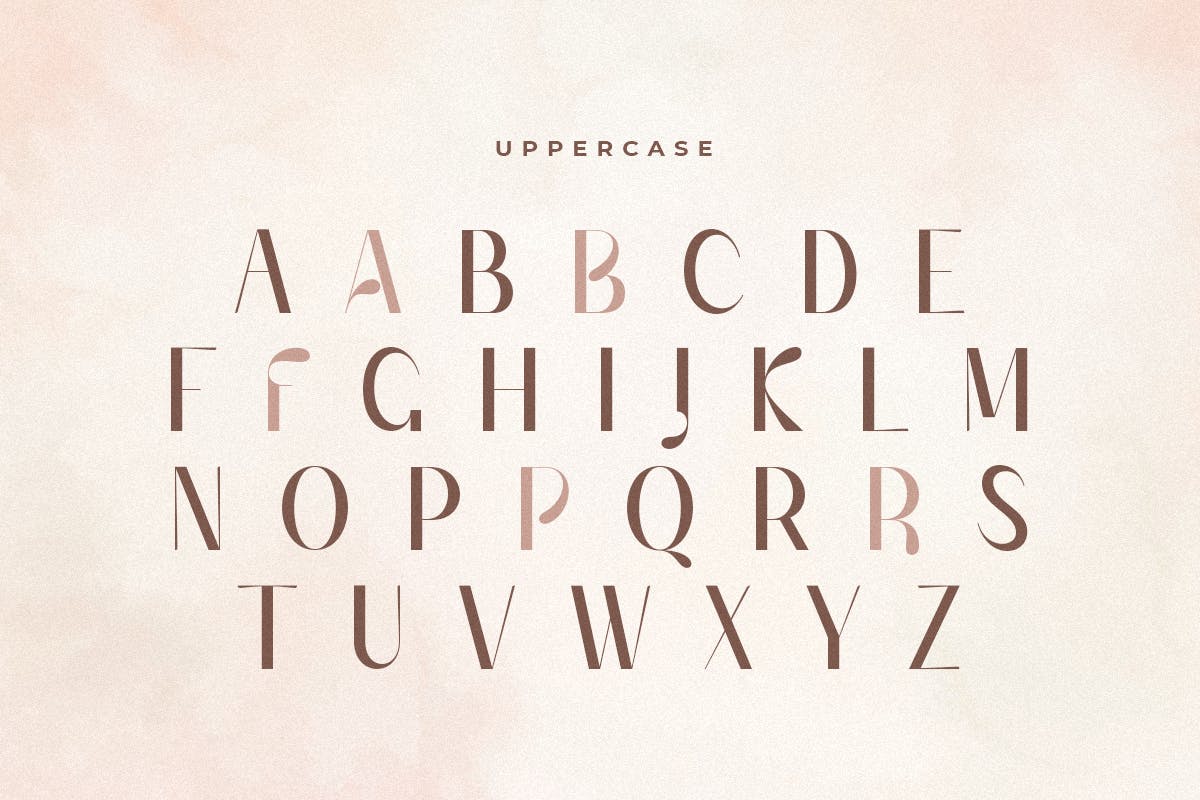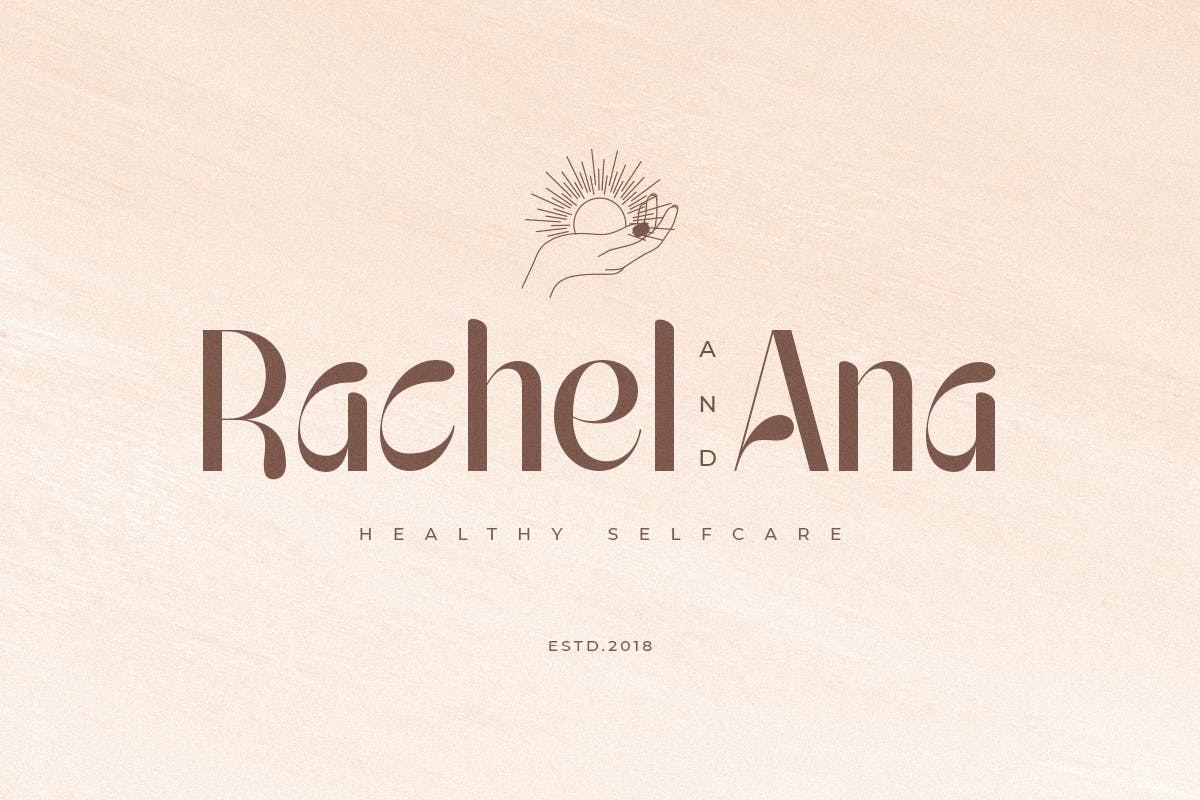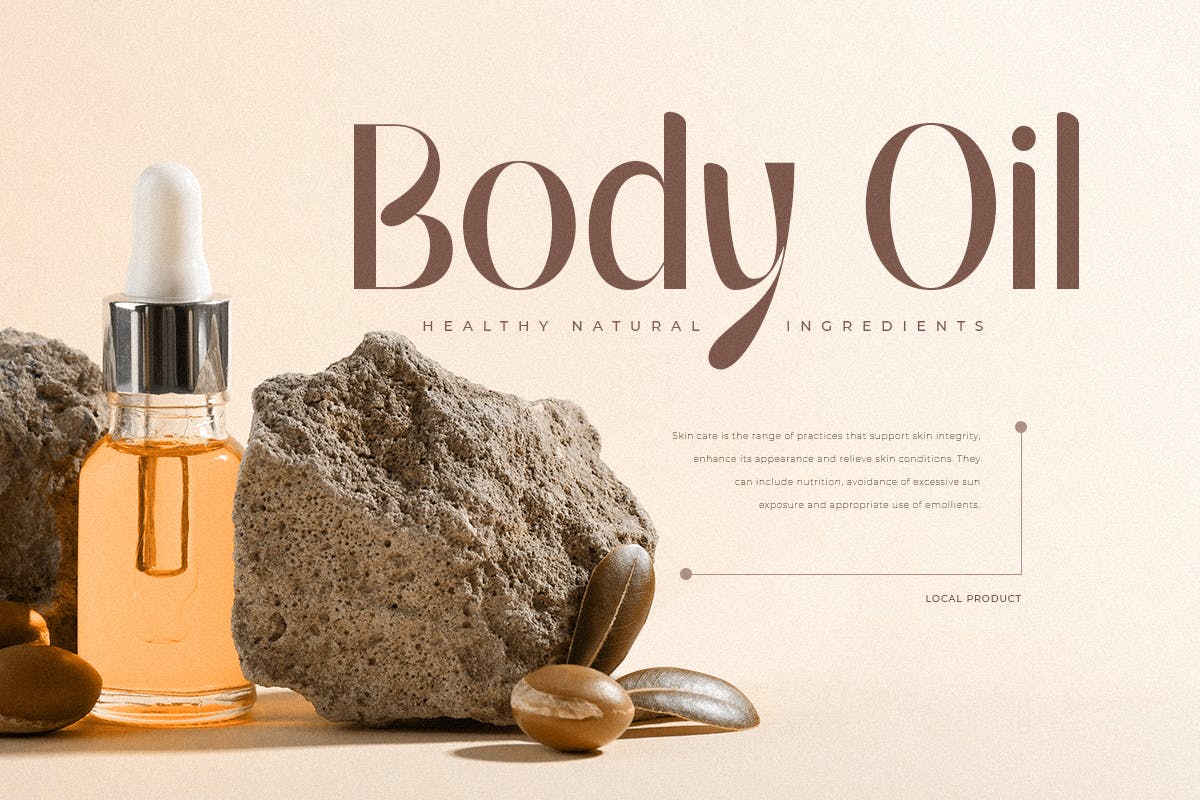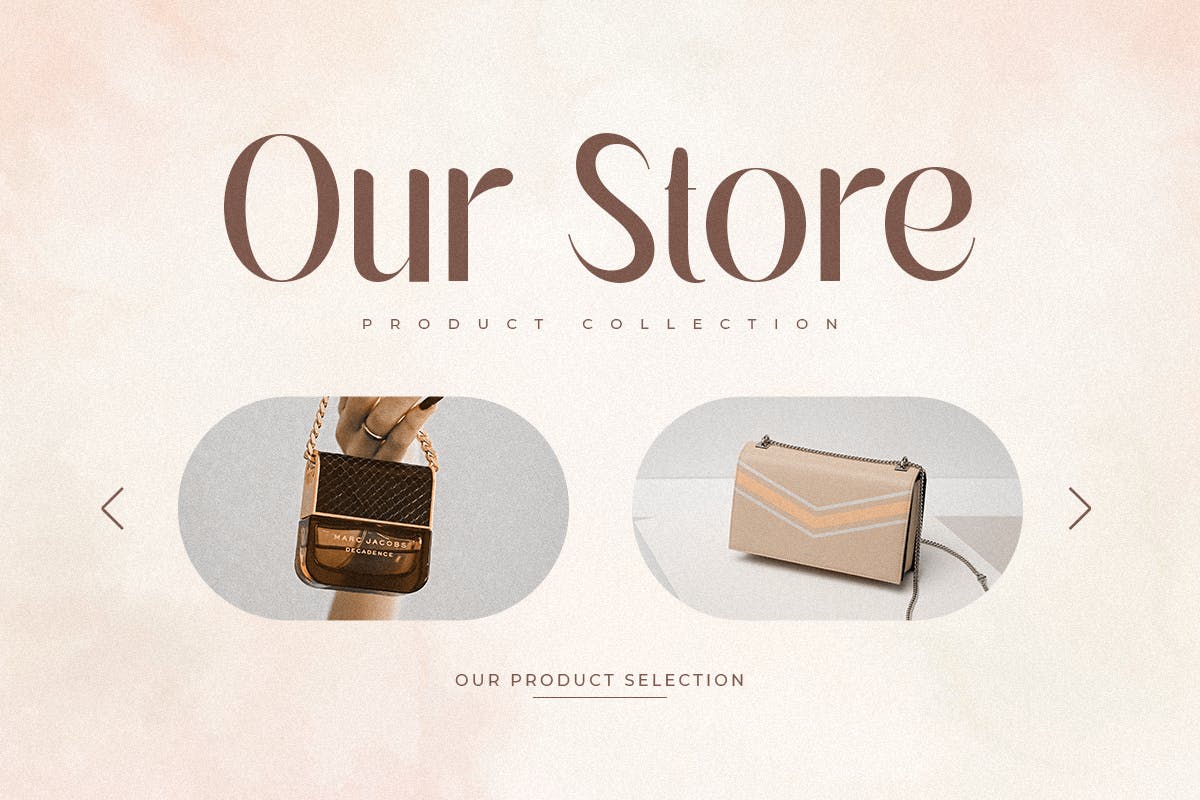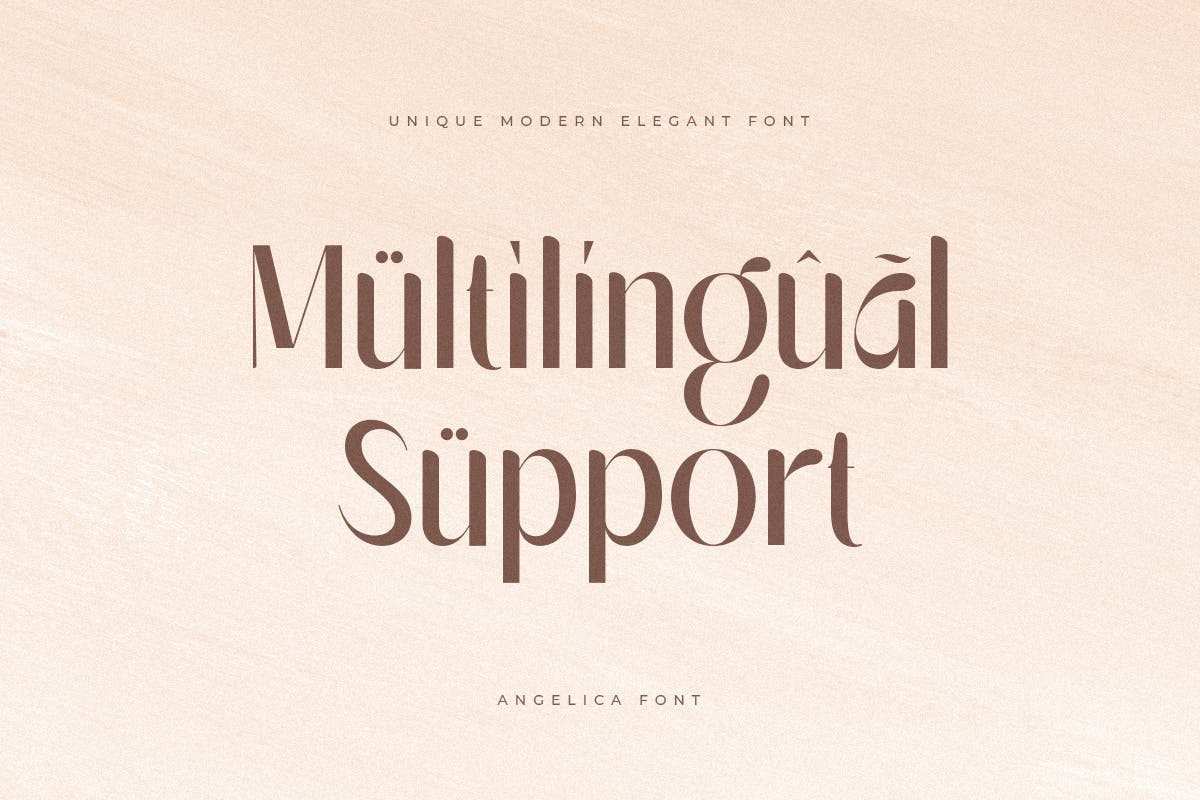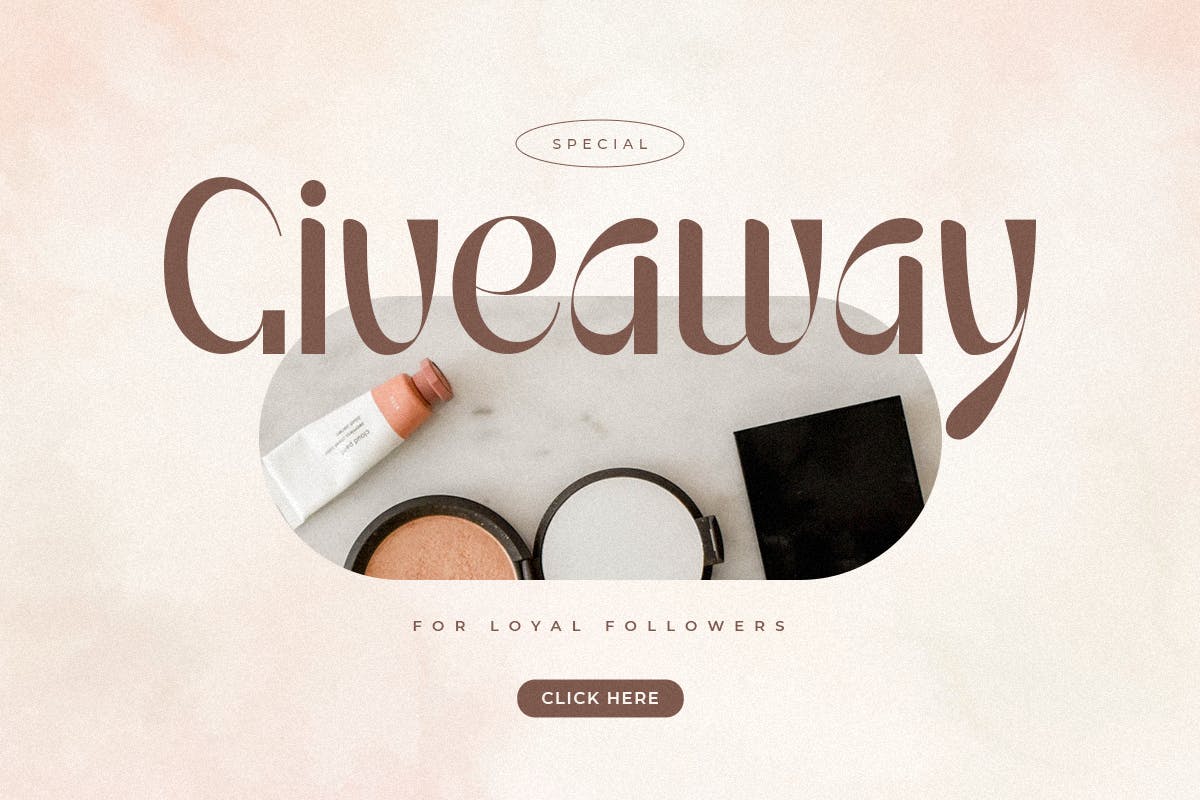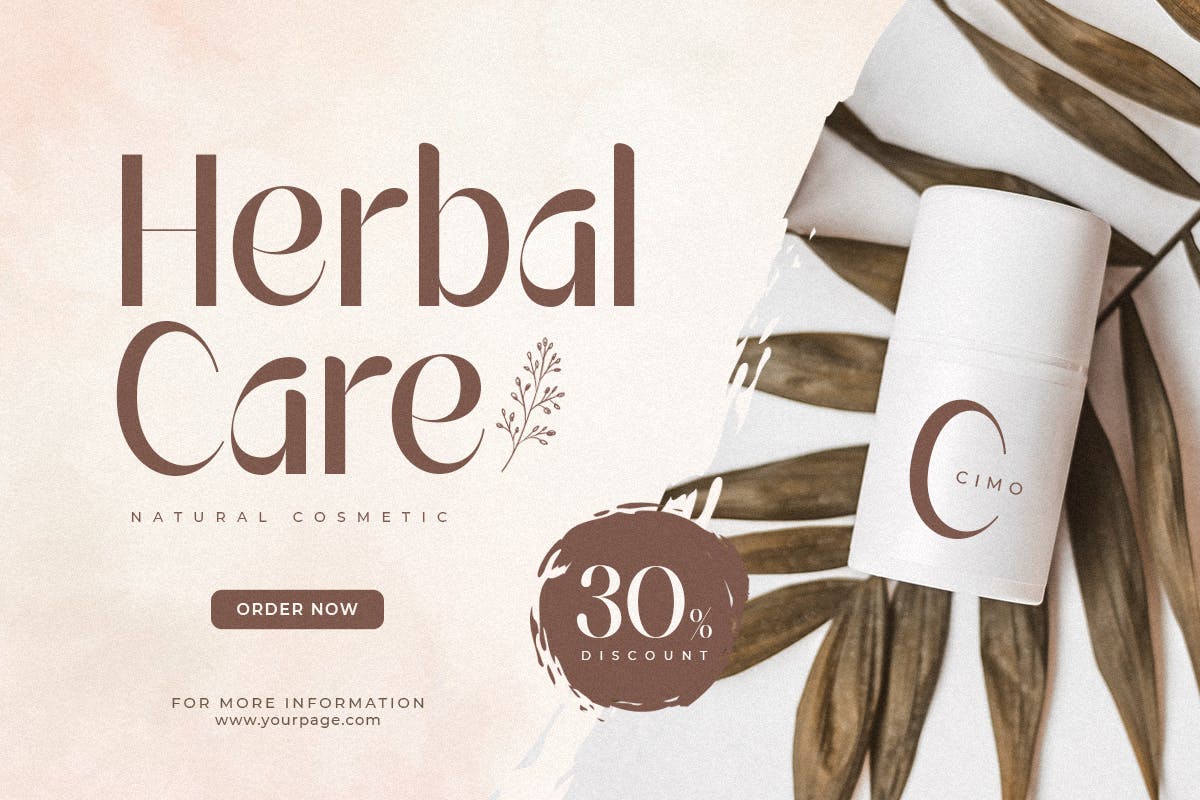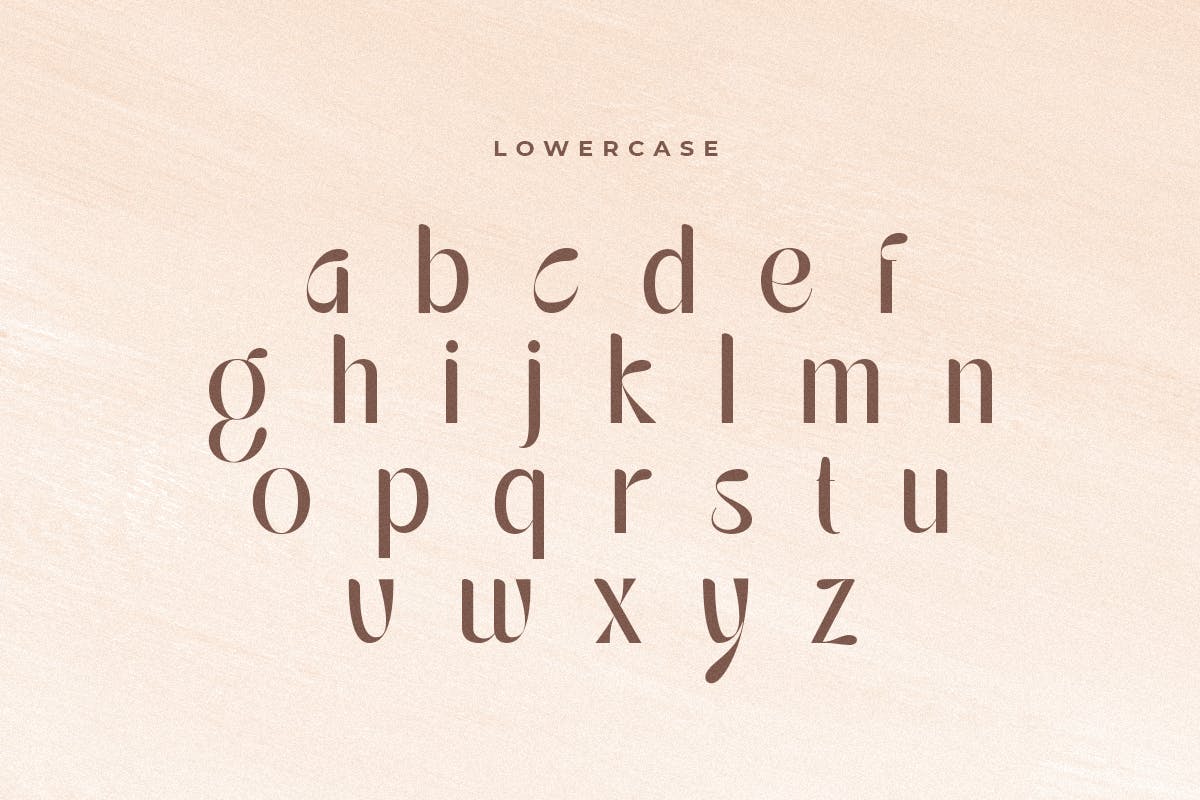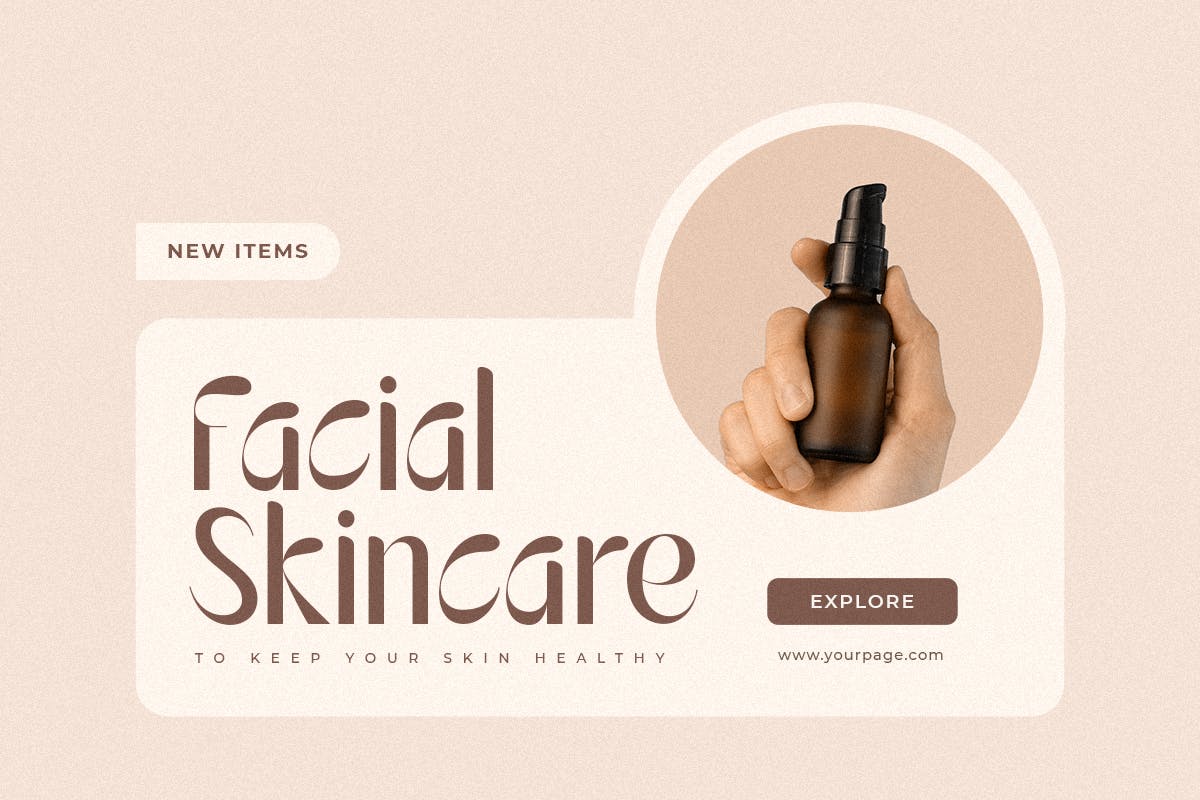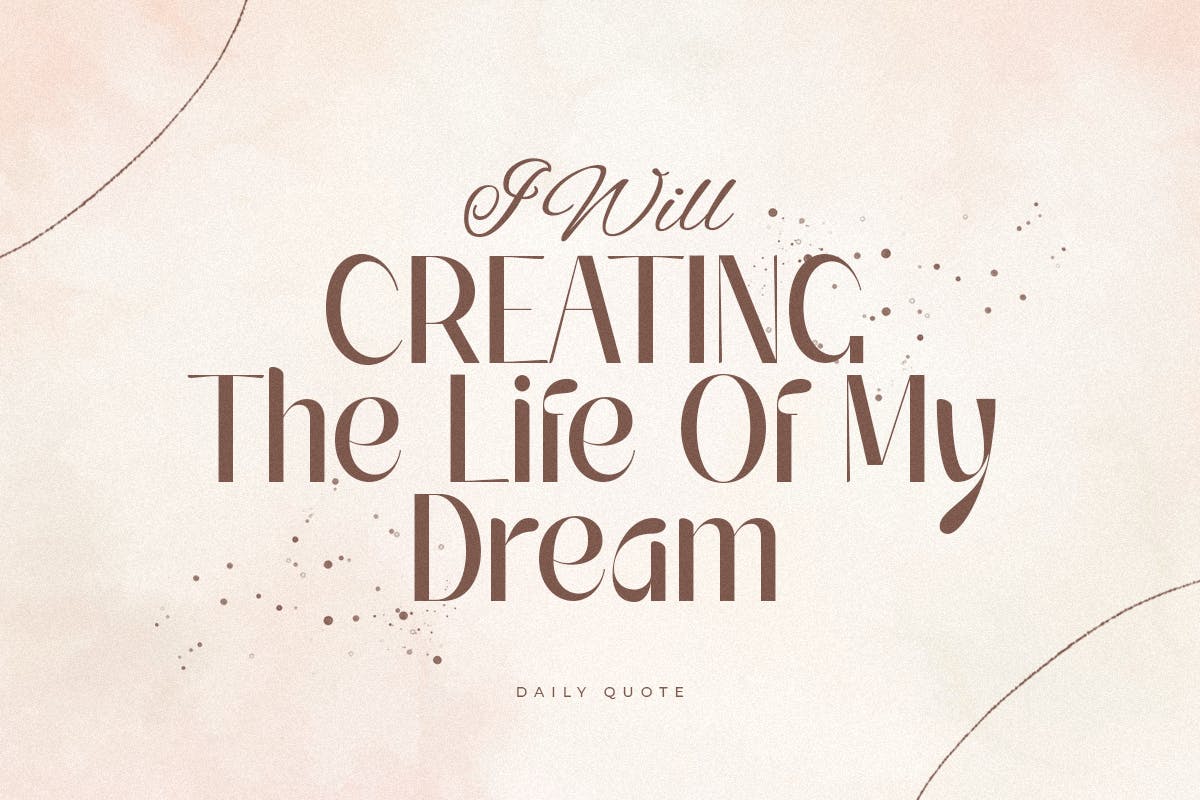
فونت آنجلیکا یک فونت مدرن و لوکس با طراحی شیک و غیررسمی است. این فونت برای هر نوع نیاز برندسازی مناسب است و با شکل منحصر به فرد خود میتواند ارزش برند شما را افزایش دهد. این فونت به طراحان و صاحبان محصولات کمک میکند تا طراحیهای خود را لوکس و زیبا جلوه دهند. به خصوص برای فونت آنجلیکا، ما دو وزن و شکل زیبا تهیه کردهایم تا به شما در ایجاد تنوعهای نامحدود برای نیازهای خلاقانهتان کمک کنیم.